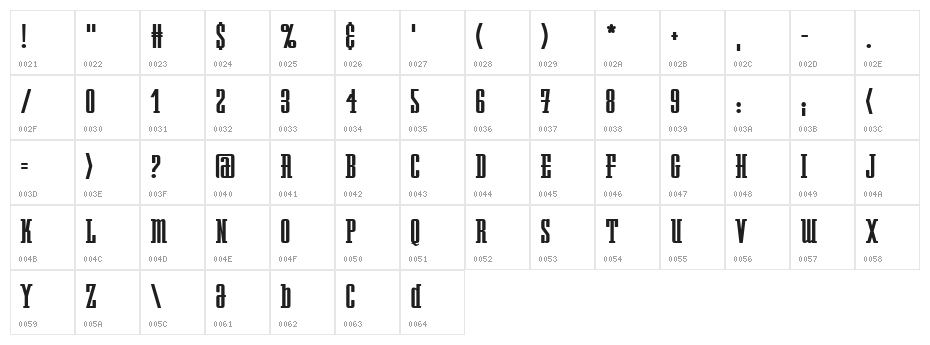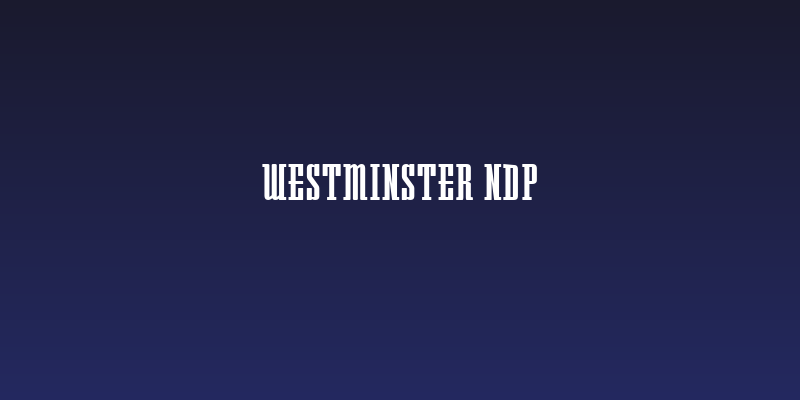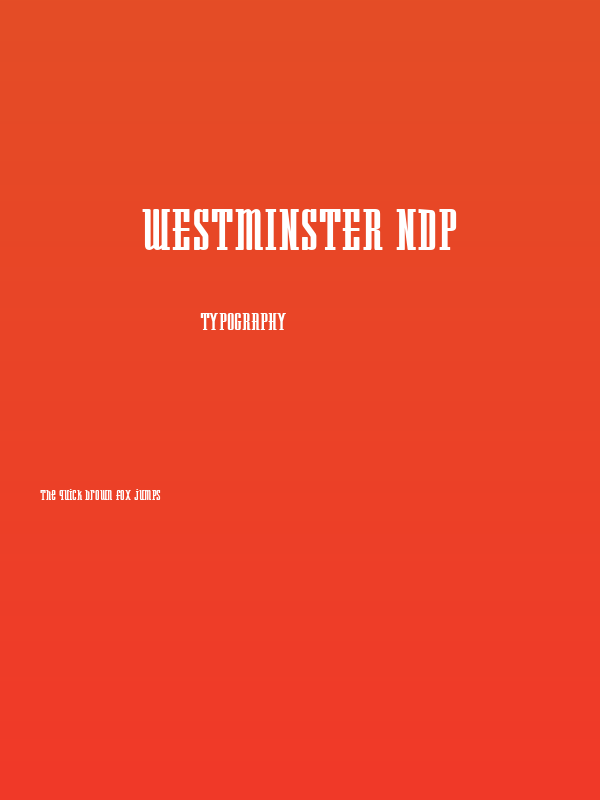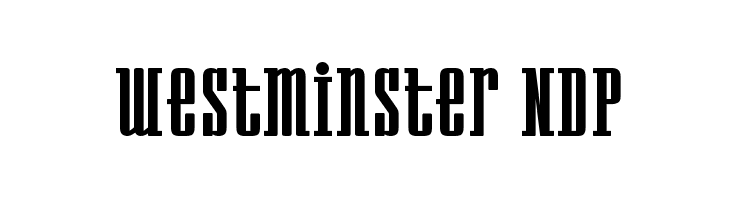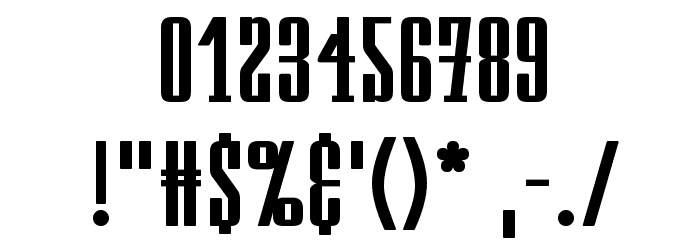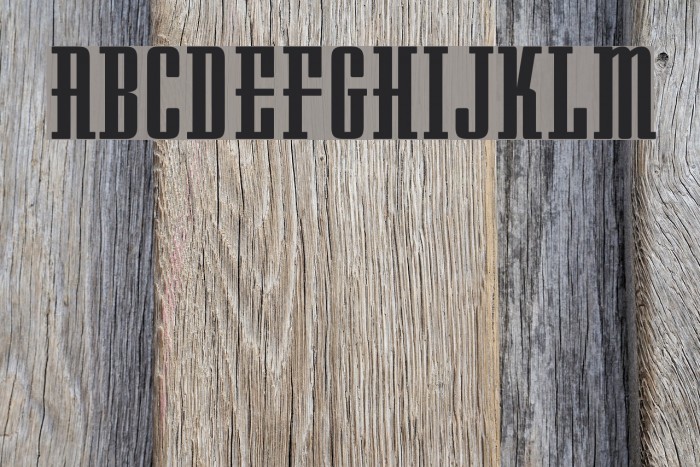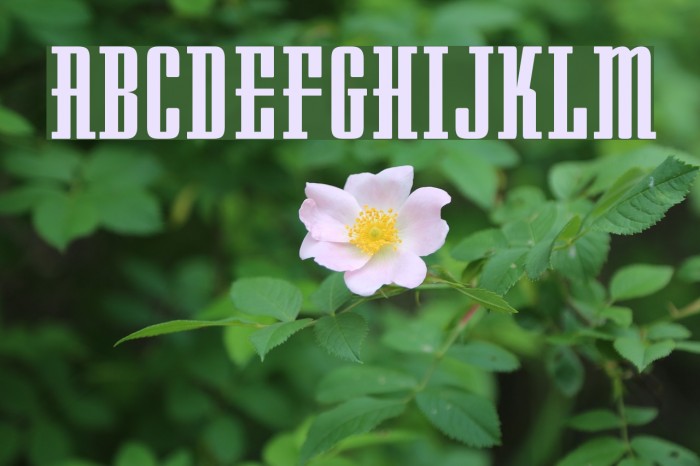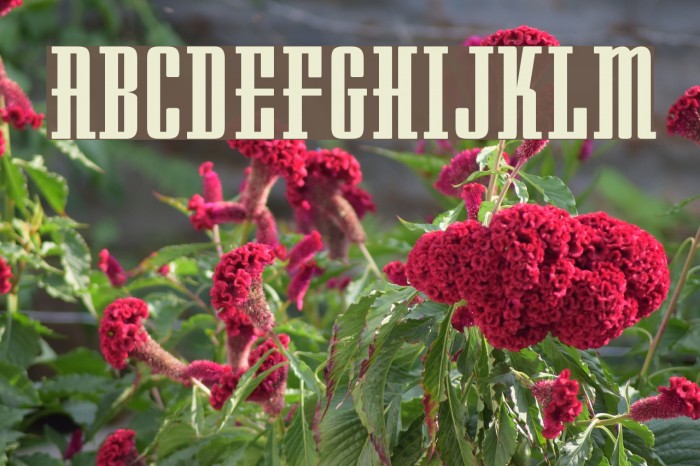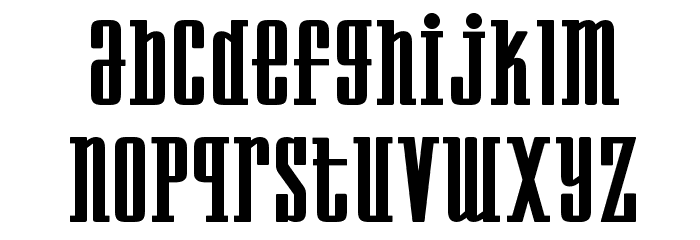
Westminster NDP Font
✎ Serif
| Gesamtstil | Vintage |
| Vorgeschlagene Projekte | Ideal for use in posters, book covers, and branding materials where a dramatic and authoritative look is desired. |